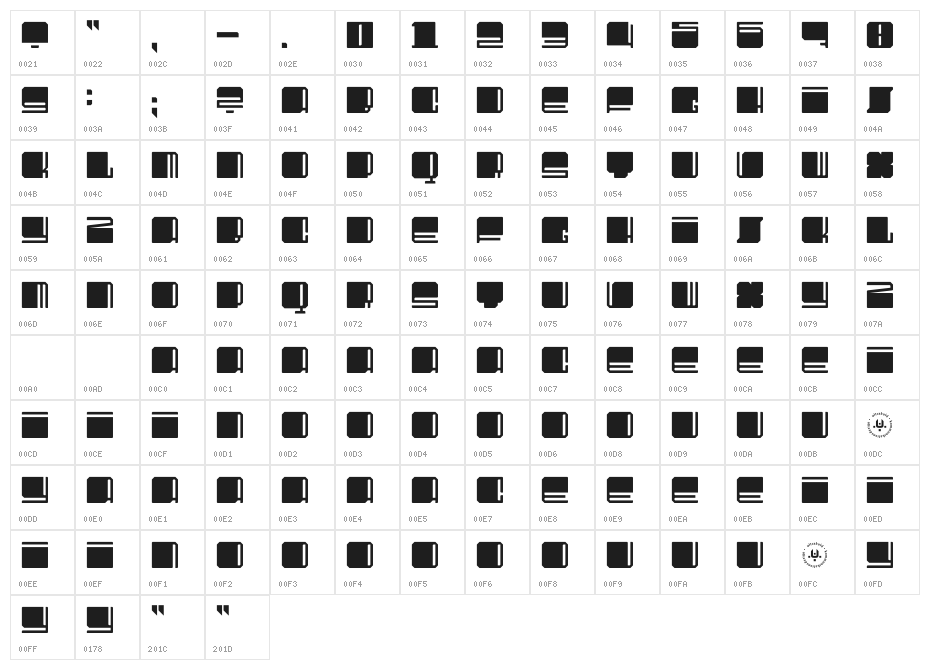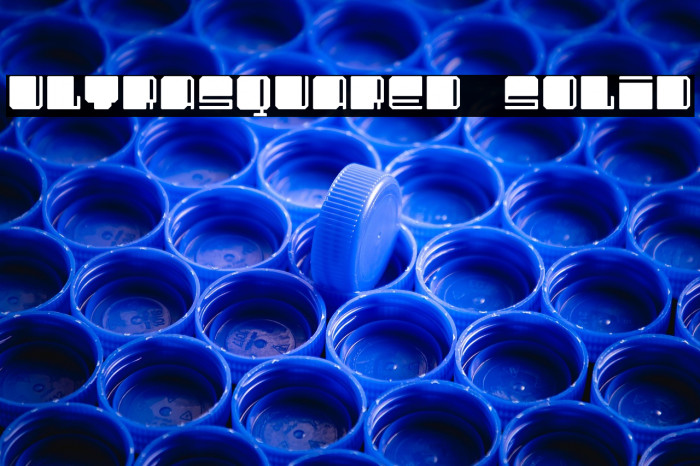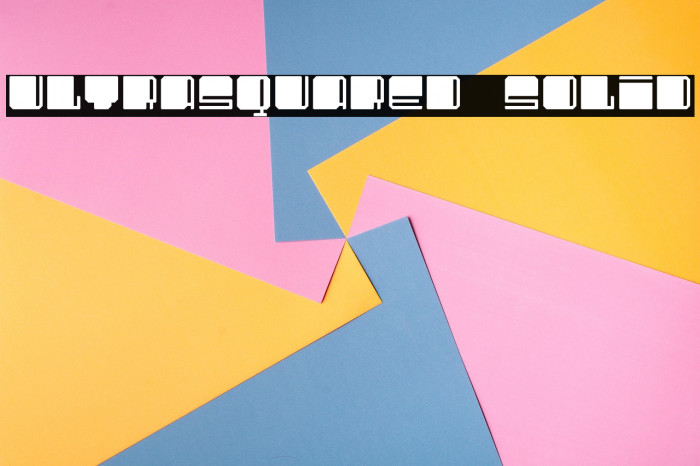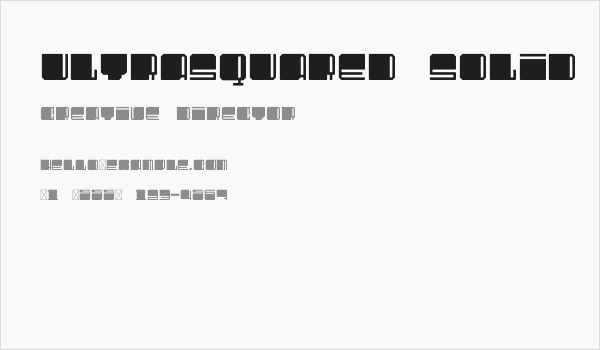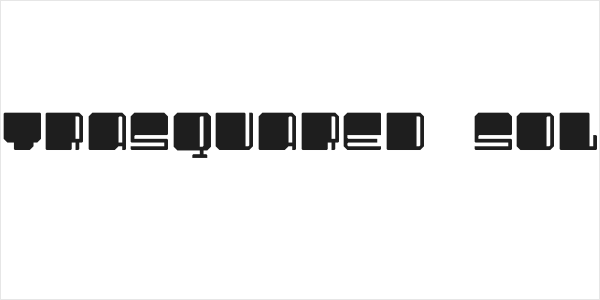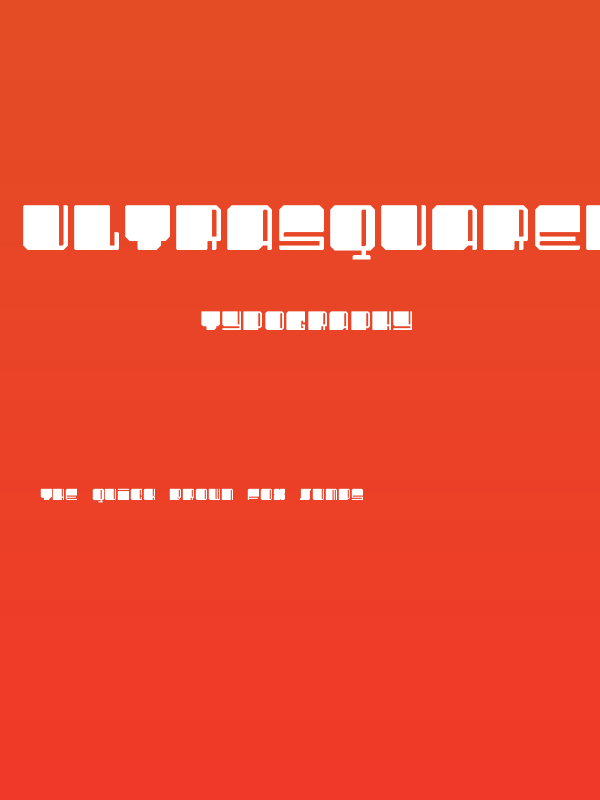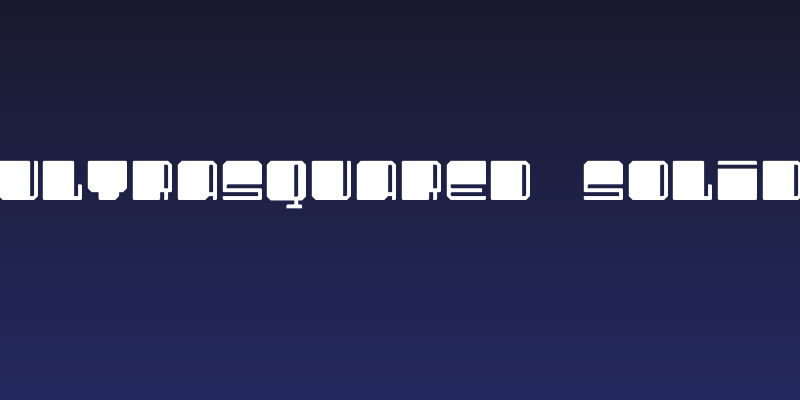
UltraSquared Solid Font
✎ Futuristic
| مشاريع مقترحة | Ideal for technology branding, futuristic posters, video game titles, and sci-fi themed projects. |